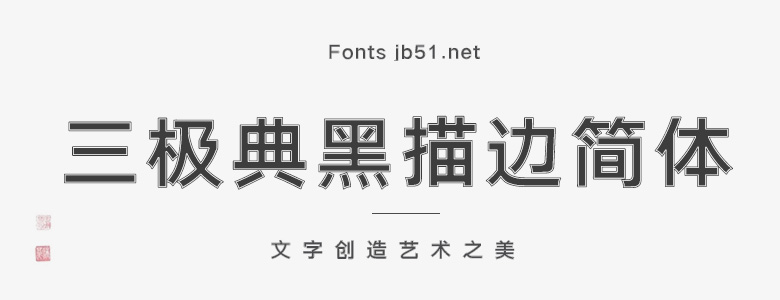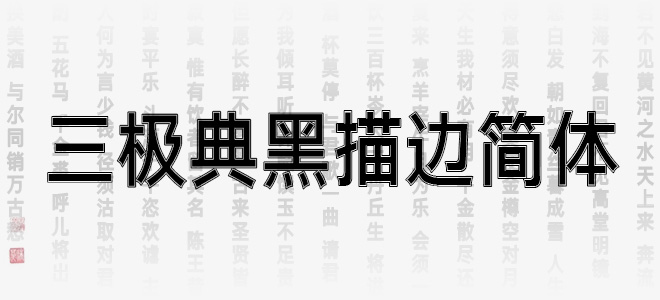
三極典黑描邊簡(jiǎn)體是一款特效字體,字形清新,結(jié)構(gòu)嚴(yán)謹(jǐn),布白均勻,中宮偏大,重心穩(wěn)定。適當(dāng)縮小字面大小、加大默認(rèn)字距、增強(qiáng)了字體的識(shí)別性,使得版面更加生動(dòng)。字形更加賦予變化。適用于各類便攜式屏幕的系統(tǒng)嵌入字體,使其形態(tài)豐富,更適用于傳統(tǒng)印刷媒介的標(biāo)題與正文排版。在品牌形象設(shè)計(jì)中作為logo設(shè)計(jì)性文字視覺(jué)效果更佳。歡迎喜歡三極典黑描邊簡(jiǎn)體的朋友前來(lái)下載使用。
三極典黑描邊簡(jiǎn)體